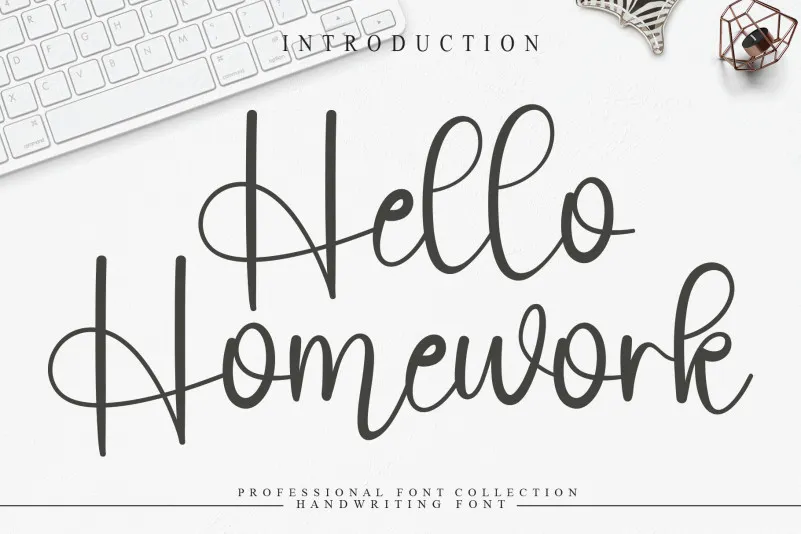
Hello Homework Script Font – Download Grátis
Aproveite a oportunidade única para dar vida à sua escrita com a Hello Homework Script Font, uma fonte de escrita manual criada pela designer creativeletter. Esta fonte é ideal para quem busca um toque especial e único em seus projetos digitais ou impressos. Com detalhes cuidadosamente desenvolvidos por creativeletter, a Hello Homework Script oferece uma experiência única que vai além do simples texto digitalizado. Suas linhas suaves e personalizadas permitem que seu texto seja não apenas legível, mas também se torne um verdadeiro elemento de design. Esta fonte é perfeita para trabalhos pessoais ou profissionais, seja em cartões de aniversário, resenhas de livros, blogs, ou até mesmo materiais educacionais. Incluído no catálogo de produtos são várias amostras e exemplos de como a Hello Homework Script pode ser aplicada. Teste-a agora para descobrir o seu próprio toque pessoal e original na escrita digital. Com ela, seu trabalho não terá mais limites quanto à personalização e expressão visual.